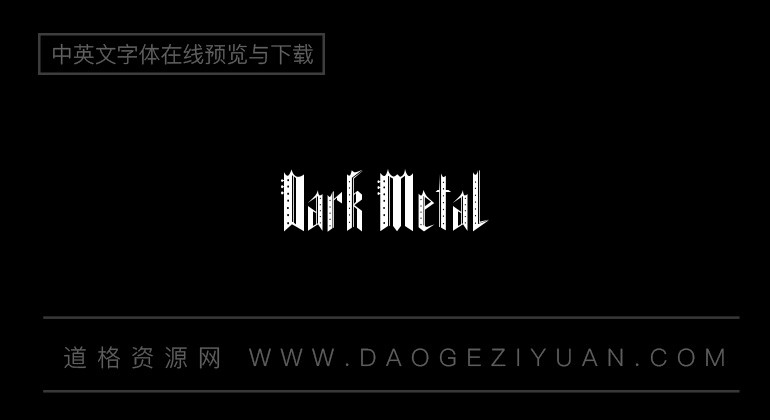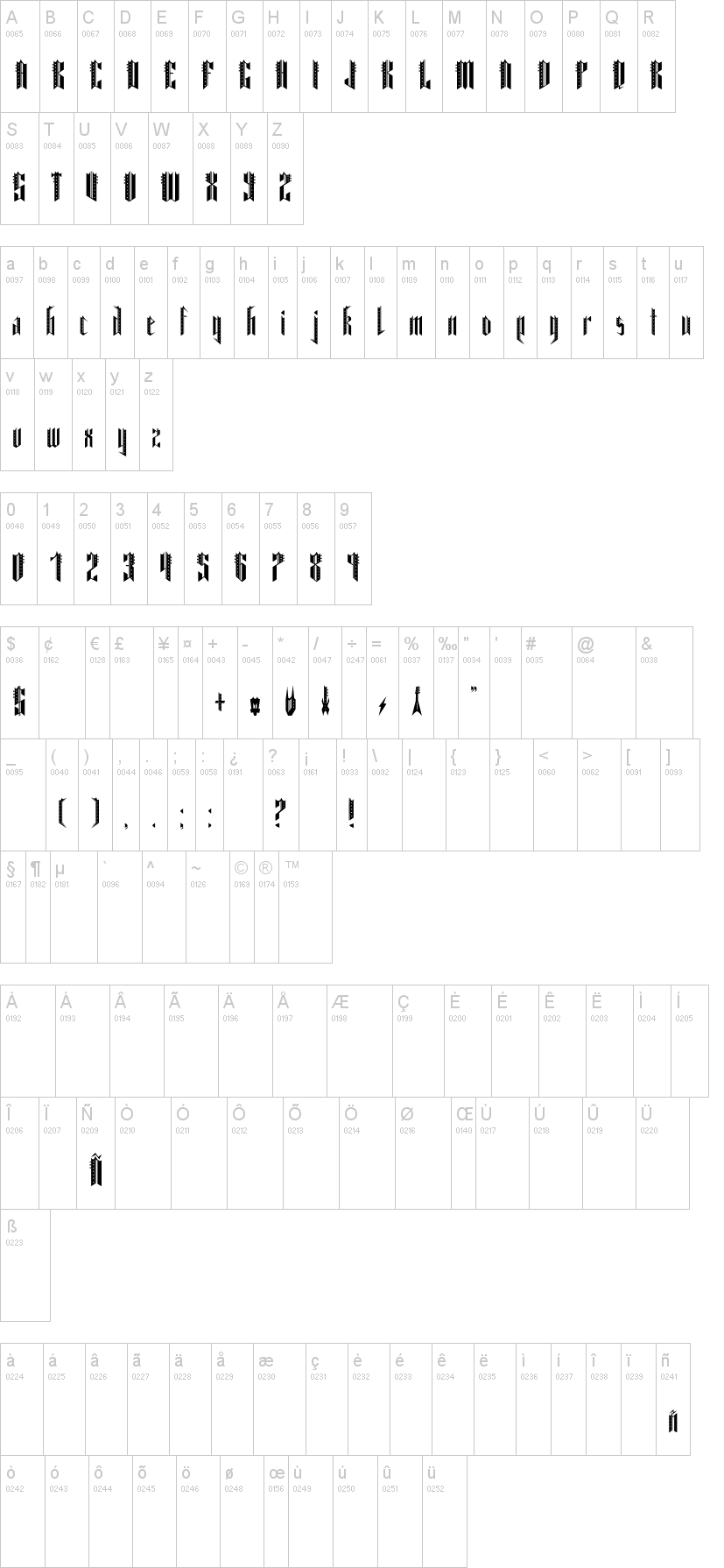
Dark Metal 是一款具有浓重金属风格的字体,它的设计灵感来源于摇滚乐和重金属音乐的视觉风格。这款字体的特点之一就是它的字母形态非常有力量感,线条笔直粗细均匀,字母之间的间距和间隔都比较大,让整体的排版效果非常醒目。Dark Metal 字体的颜色通常为深灰色或黑色,充满神秘感和未知的吸引力。这种字体适合用于涉及摇滚、金属、暴力或恐怖等主题的设计作品,如海报、音乐专辑封面、游戏界面等。内容介绍
Dark Metal是一款非常不错的手写艺术字体,具有很好的视觉感,适合于文化类的宣传设计、商业类品牌的广告和产品包装设计以及个性化文字排版等较多场景。